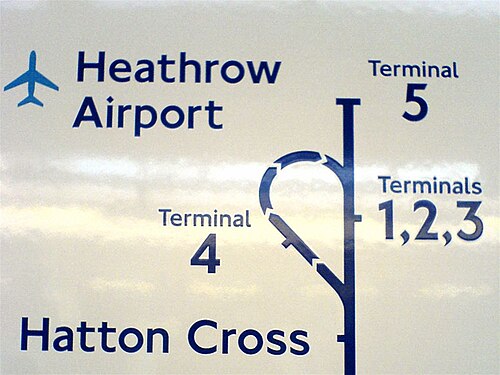
جونستون (نوع الخط)
جونستون (أو جونستون سانس ) هو خط طباعي بدون زوائد، صممه إدوارد جونستون وسُمي تيمناً به . وقد طُلب تصميم هذا الخط عام ١٩١٣ من قبل فرانك بيك ، المدير التجاري لشركة مترو أنفاق لندن (المعروفة أيضاً باسم "مجموعة المترو")، كجزء من خطته لتعزيز هوية الشركة . [ ١ ] صُمم خط جونستون في الأصل للطباعة (بارتفاع مُخطط له يبلغ بوصة واحدة أو ٢.٥ سم)، ولكنه سرعان ما استُخدم أيضاً في لافتات محطات المترو المطلية بالمينا. [ ٢ ]
كان هذا الخط هو الخط الرسمي لوسائل النقل العام في لندن منذ تأسيس مجلس نقل الركاب في لندن عام 1933، وللشركات السابقة منذ تقديمه عام 1916، مما يجعل استخدامه أحد أطول الأمثلة استمرارًا في العالم على العلامات التجارية للشركات . وكان هذا الخط ملكية فكرية محمية لشركة النقل في لندن، خلف مجلس نقل الركاب في لندن ، حتى يوم الملكية العامة عام 2015 (توفي جونستون عام 1944).
ابتكر جونستون نوعًا جديدًا من الخطوط الإنسانية الخالية من الزوائد ، وهي خطوط مستوحاة من الخطوط التقليدية ذات الزوائد والنقوش الرومانية. وقد استخدمها تلميذه إريك جيل ، الذي عمل على تطوير هذا الخط، كنموذج لخطه الخاص "جيل سانس" الذي صدر عام ١٩٢٨. وباعتباره خطًا خاصًا بالشركات، لم يكن جونستون متاحًا للترخيص العام إلا مؤخرًا، ولذلك أصبح "جيل سانس" أكثر استخدامًا. [ ٣ ]
سمات
تستند الأحرف الكبيرة في هذا الخط إلى الأحرف الرومانية المربعة الكبيرة، كتلك الموجودة على عمود تراجان ، بينما تستند الأحرف الصغيرة إلى الخطوط التقليدية ذات الزوائد. كان جونستون معجبًا جدًا بالأحرف الرومانية الكبيرة، وكتب أنها "تحتل مكانة سامية بين الأحرف من حيث سهولة القراءة والجمال. إنها أفضل الأشكال لأعظم النقوش وأكثرها أهمية." [ 5 ] وقد سلط جاستن هاوز ، مؤلف العمل الرائد حول تصميم خط جونستون سانس، " خط جونستون السري "، الضوء على تشابه التصميم مع خط كاسلون الذي صممه ويليام كاسلون في القرن الثامن عشر على وجه الخصوص، مشيرًا إلى أن جونستون عمل على كتاب طُبع باستخدام هذا الخط قبل فترة وجيزة من بدء العمل على تصميمه، وقام بإعادة إنتاج بنيته في كتاب مدرسي. [ 6 ]
مثّلت أبجدية جونستون قطيعةً مع أنواع الخطوط غير المزخرفة الشائعة آنذاك، والمعروفة الآن باسم الخطوط الغروتسكية ، والتي كانت تميل إلى الأشكال المربعة المستوحاة من كتابة اللافتات ونمط ديدون في تلك الفترة. تتسم بعض جوانب الأبجدية بطابع هندسي: فالحرف O عبارة عن دائرة شبه كاملة، والحرف M، على عكس الأحرف الرومانية الكبيرة (ولكن مثل كاسلون)، ذو جوانب مستقيمة. [ 7 ] وكما هو الحال في معظم الخطوط المزخرفة، فإن الحرف g مصمم على شكل "طابقين". أما الحرف l فيحاكي انحناءة الحرف t، مما ينتج عنه حرف عريض نسبيًا مقارنةً بمعظم الخطوط غير المزخرفة. [ 8 ] ويحتوي الحرفان i و j الصغيران على نقاط مربعة موضوعة قطريًا ، وهو نمط يتكرر في بعض النسخ الرقمية في النقطة ، والفاصلة ، وعلامات الترقيم الأخرى .
أخذت عملية تصميم جونستون في الاعتبار مجموعة متنوعة من الخصائص غير المألوفة، مثل كتابة حرف "q" كبير في الأحرف الصغيرة وحرف "a" أحادي الطبقة كما ظهر لاحقًا في خط فوتورا ، قبل أن تتخلى عنها في النهاية لصالح تصميم نظيف وبسيط. [ 5 ] [ 9 ] [ a ] ومع ذلك، تضمنت العديد من الإصدارات المبكرة من "أبجدية" جونستون حرف "W" على غرار خط غاراموند مكونًا من حرفي "V" متقاطعين، وأظهرت بعض الرسومات المبكرة المكتوبة بخط اليد تنوعًا.
على عكس العديد من الخطوط غير المزخرفة في تلك الفترة، فإن تصميم جونستون (مع أنه ليس نحيفًا) ليس جريئًا بشكل خاص. وقد كتب جيل لاحقًا عن إعجابه بكيفية "إنقاذ" جونستون للخطوط غير المزخرفة من "فساد القرن التاسع عشر" المتمثل في الجرأة المفرطة. [ 5 ] [ 11 ]
صُمم خط جونستون، باعتباره أبجدية مخصصة للوحات الإرشادية، بدون أي حروف مائلة . لذا، فإن أي تصميم مائل يُرى هو من ابتكار مصمم لاحق، بهدف مطابقة تصميم جونستون. وقد اختار مصممون مختلفون مناهج متباينة لتحقيق ذلك: فمنهم من قدم خطًا مائلًا "حقيقيًا"، ومنهم من قدم خطًا مائلًا حيث تكون الحروف مائلة ببساطة، ومنهم من رفض تقديمه، ربما لاعتقاده أن الخط المائل غير مناسب لغرض التصميم الأصلي. [ 12 ] [ 13 ] وقد كلفت هيئة النقل في لندن بيرتولد وولبي بتصميم نسخة رسمية من الخط المائل عام 1973. [ 14 ]
تاريخ
أبدى جونستون اهتمامًا بالحروف غير المزخرفة قبل سنوات من تكليفه بهذا العمل؛ فرغم شهرته كخطاط، فقد كتب وعمل أيضًا على تصميم حروف مخصصة، وفي كتابه المدرسي " الكتابة والتذهيب وتصميم الحروف" الصادر عام ١٩٠٦ ، أشار إلى أنه "من الممكن تمامًا ابتكار أبجدية جميلة ومميزة من حروف متساوية السماكة، على غرار ما يُسمى بـ"الحروف المطبوعة" [الحروف غير المزخرفة الشائعة في ذلك الوقت] ولكن بنسب وتشطيبات مناسبة." [ ١٥ ] كما كتب في ربيع عام ١٩١٣ أن الكتب الجديدة يجب أن "تحمل بصمة حية للعصر الذي نعيش فيه". وكان جونستون قد حاول سابقًا، دون جدوى، دخول مجال تصميم الخطوط، وهو مجال كان يُصمم فيه عادةً داخل المؤسسة. وكتب هاوز أن خط جونستون كان "أول خط يُصمم للاستخدام اليومي من قِبل فنان حرفي بارز." [ ١٦ ]
حدد بيك لجونستون أنه يريد خطًا يضمن عدم الخلط بين ملصقات مجموعة مترو الأنفاق والإعلانات؛ إذ يجب أن يتميز بـ"البساطة الجريئة للحروف الأصلية في أرقى العصور" وأن ينتمي "بشكل لا لبس فيه إلى القرن العشرين". [ 17 ] وقد رأى بيك أن الخط غير المزخرف هو الأنسب للاستخدام في وسائل النقل، وخلص إلى أن حروف عمود تراجان الكبيرة غير مناسبة للطباعة على الأسطح المستوية. [ 18 ]
في عام ١٩٣٣، تم دمج مجموعة مترو الأنفاق مع مجلس نقل ركاب لندن ، واعتُمد الخط كجزء من هوية هيئة نقل لندن . وفي وقت مبكر من عام ١٩٣٧، ذكر مجلس نقل ركاب لندن هذا الخط ضمن حزمة ترويجية للوحات الإعلانية الخاصة بالنظام، كمثال على التزامه بالتصميم الأنيق، إلى جانب تكليفه الفنان فيليكس توبولسكي برسم لوحة فنية . [ ٨ ] ولا تزال رسومات جونستون محفوظة في متحف فيكتوريا وألبرت .
جاء تصميم جونستون الأصلي بنوعين من الخطوط، عادي وسميك ، وسرعان ما ظهرت الأحرف المكثفة لاستخدامها على الحافلات لعرض المسارات والوجهات. لا يحتوي الخط السميك على أحرف صغيرة. [ 19 ] كما عمل جونستون على تصميمات حروف وعلامات تجارية أخرى لنظام مترو الأنفاق، وأشهرها شعار "الخط والدائرة" الدائري الذي لا يزال مترو الأنفاق يستخدمه (وهو تصميم مُحسّن من تصميمات سابقة كان فيها الشعار أحمر اللون بالكامل). [ 20 ]